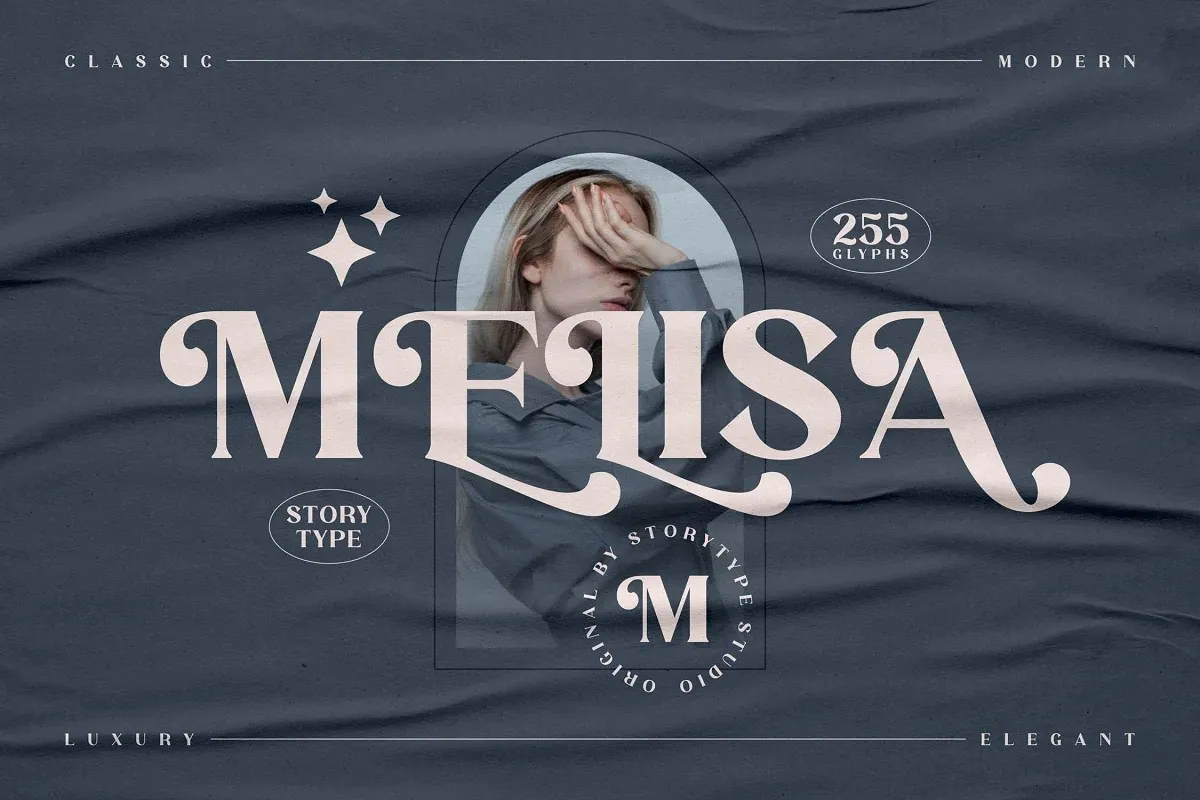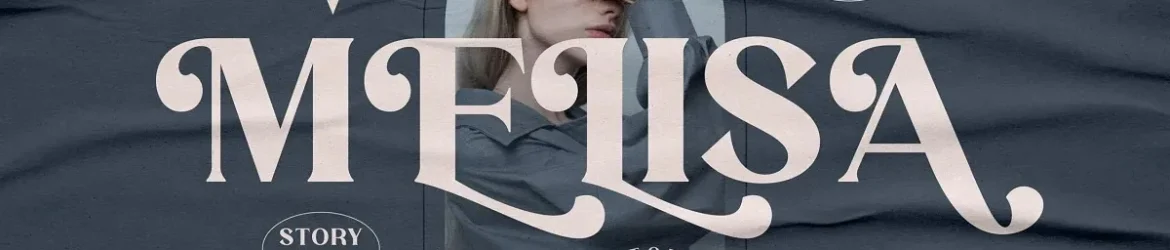
A fonte Melisa é uma tipografia serif moderna e arrasadora criada pela Storytype Studio com diversas ligaturas e alternativas. Ela se destaca para criações como logotipos elegantes e luxuosos, títulos de livros ou filmes, marcas fashionistas, capas de revista, roupas de grife, ilustrações de letra, citações e muito mais. Se você está procurando por uma fonte que transmite sofisticação e requinte para seu próximo projeto visual, a Melisa é perfeita. Seu design elegante se adapta a um amplo espectro de aplicabilidades, tornando-a uma escolha versátil para qualquer tipo de criação gráfica.